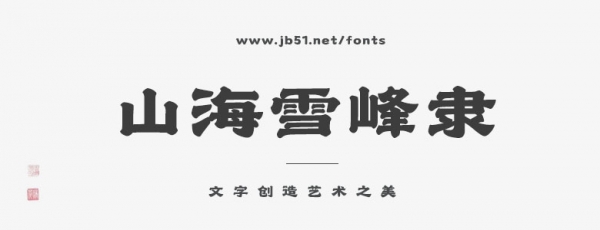
山海雪峰隸,由山海字體社出品,本字體為簡繁字庫,采用Adobe GB1-5編碼,包含常用簡體(GB2312 80) 6763個,繁體(GBK) 2406個,共計9169個漢字;以及ASCII常用西文200+。字體線條粗細(xì)適中,筆畫隨性,結(jié)構(gòu)肆意灑脫,具有很好的視覺感,適用于標(biāo)題,書刊印刷,廣告包裝設(shè)計等場景。